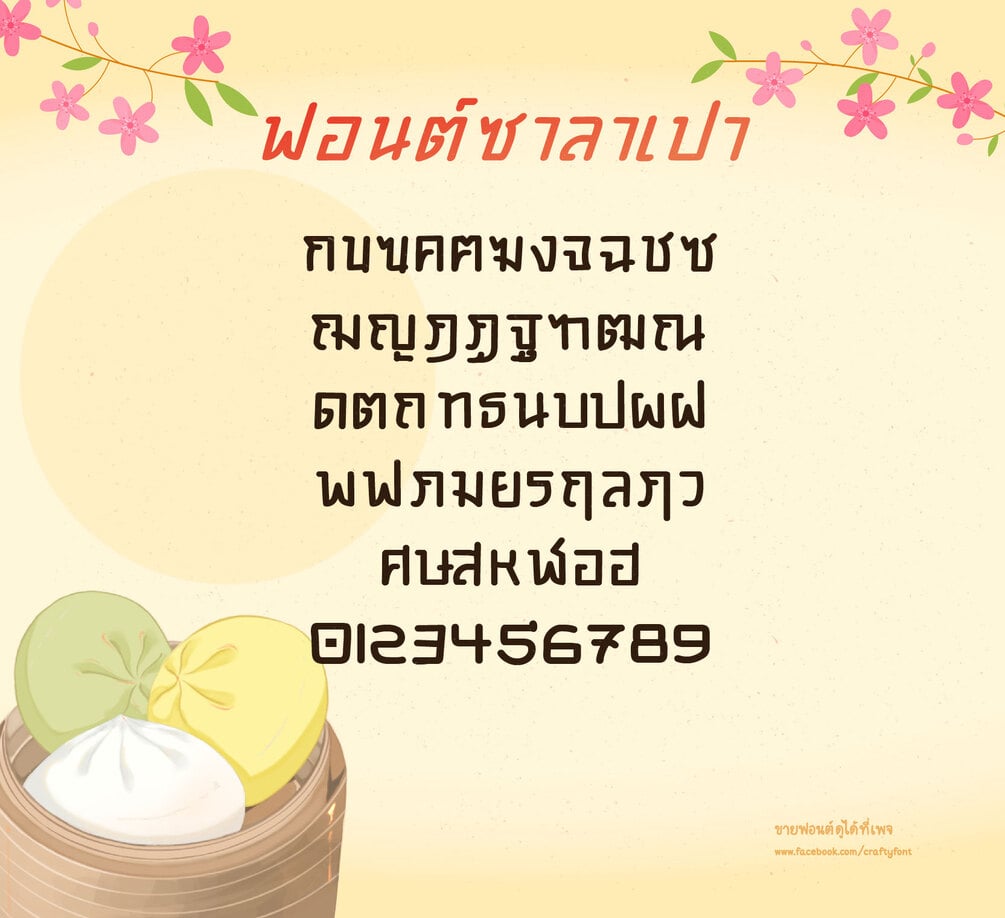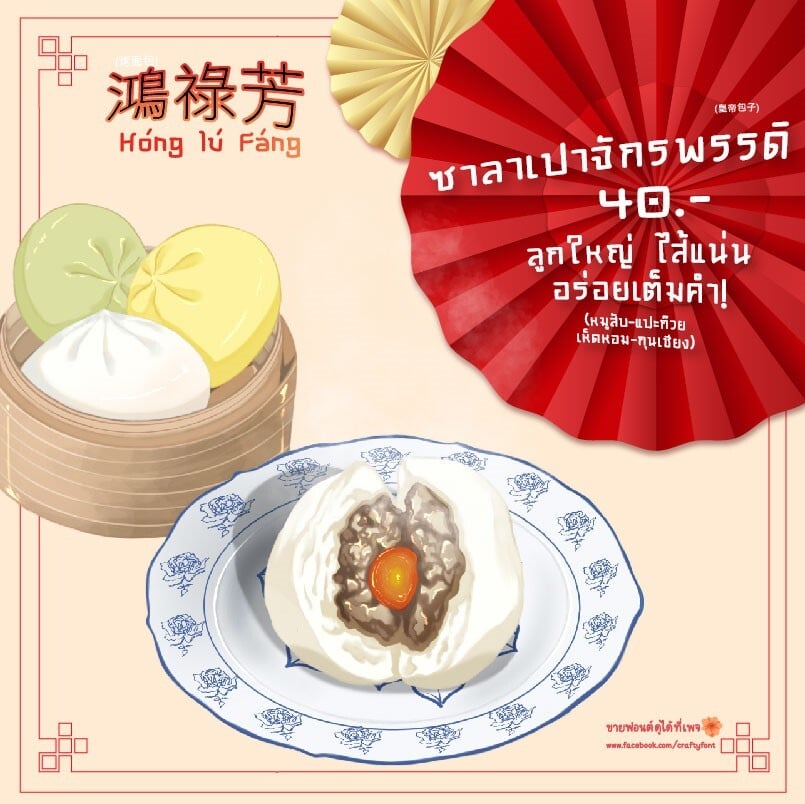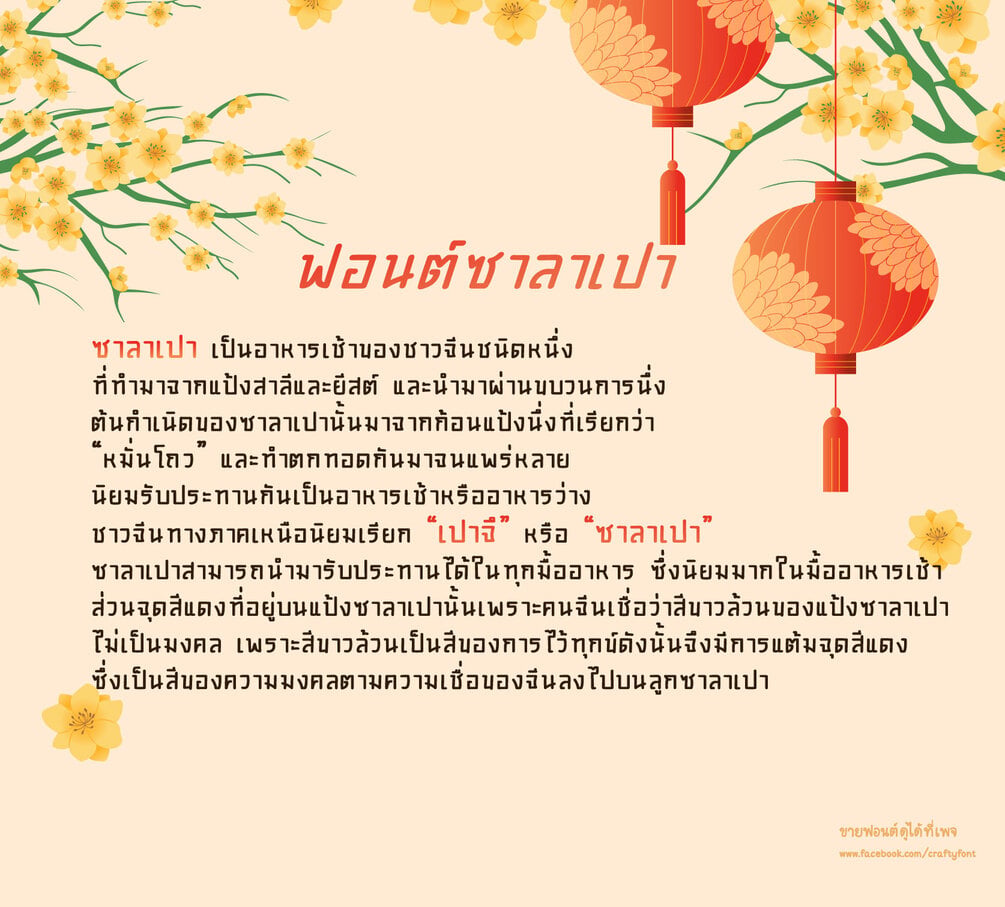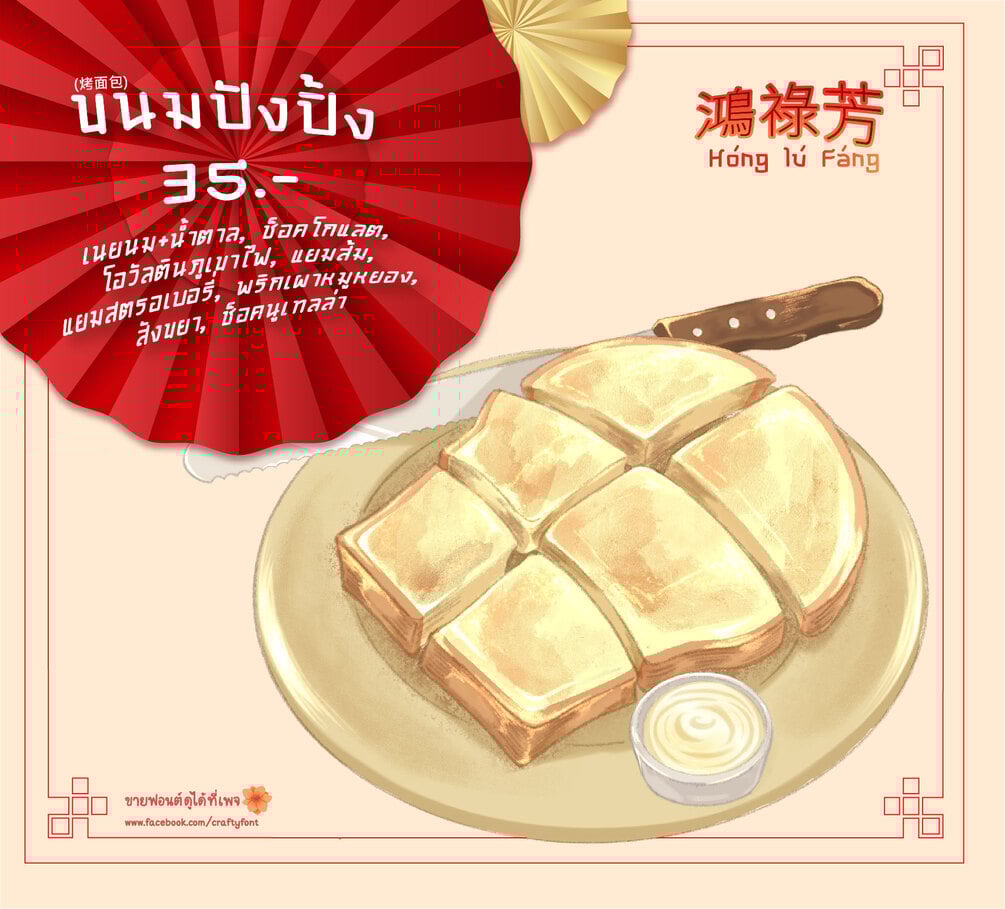
Baozi Font (ฟอนต์ซาลาเปา)
ซาลาเปาร้อนๆ จะกินแบบปอกเปลือกก็นู้มมมม หรือกินไม่ปอกก็อร่อยเต็มคำ!
ฟอนต์สไตล์ภาษาจีน มีให้ทั้งภาษาไทยและภาษาอังกฤษ มีตัวเลข และสัญลักษณ์เลยค่ะ :) (ไม่มีภาษาจีนนะ!) ฟอนต์ตัวนี้ใช้ระยะเวลาทำสั้นมาก เพราะปั่นสุดฤทธิ์ อยากให้ทันเทศกาลตรุษจีน 🥰